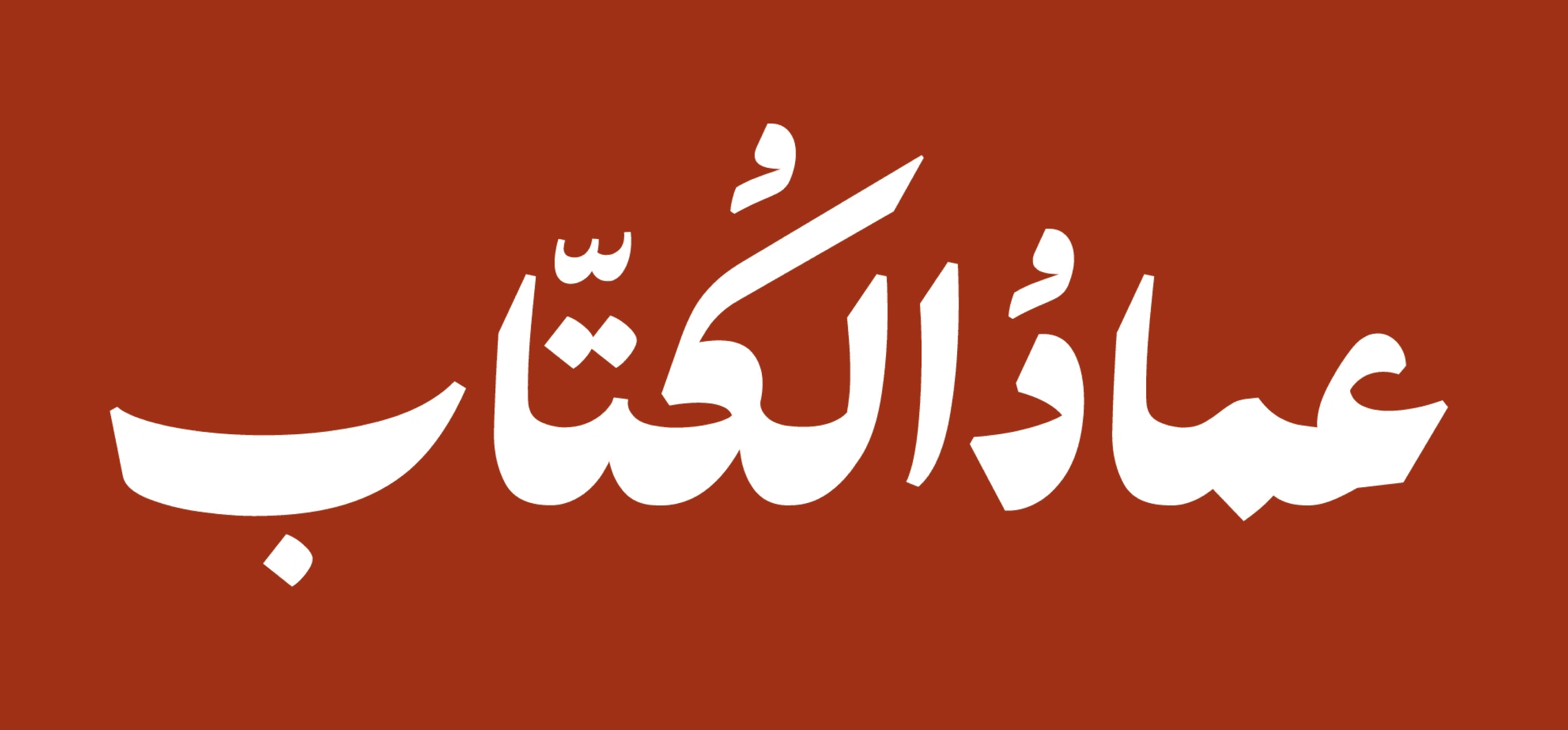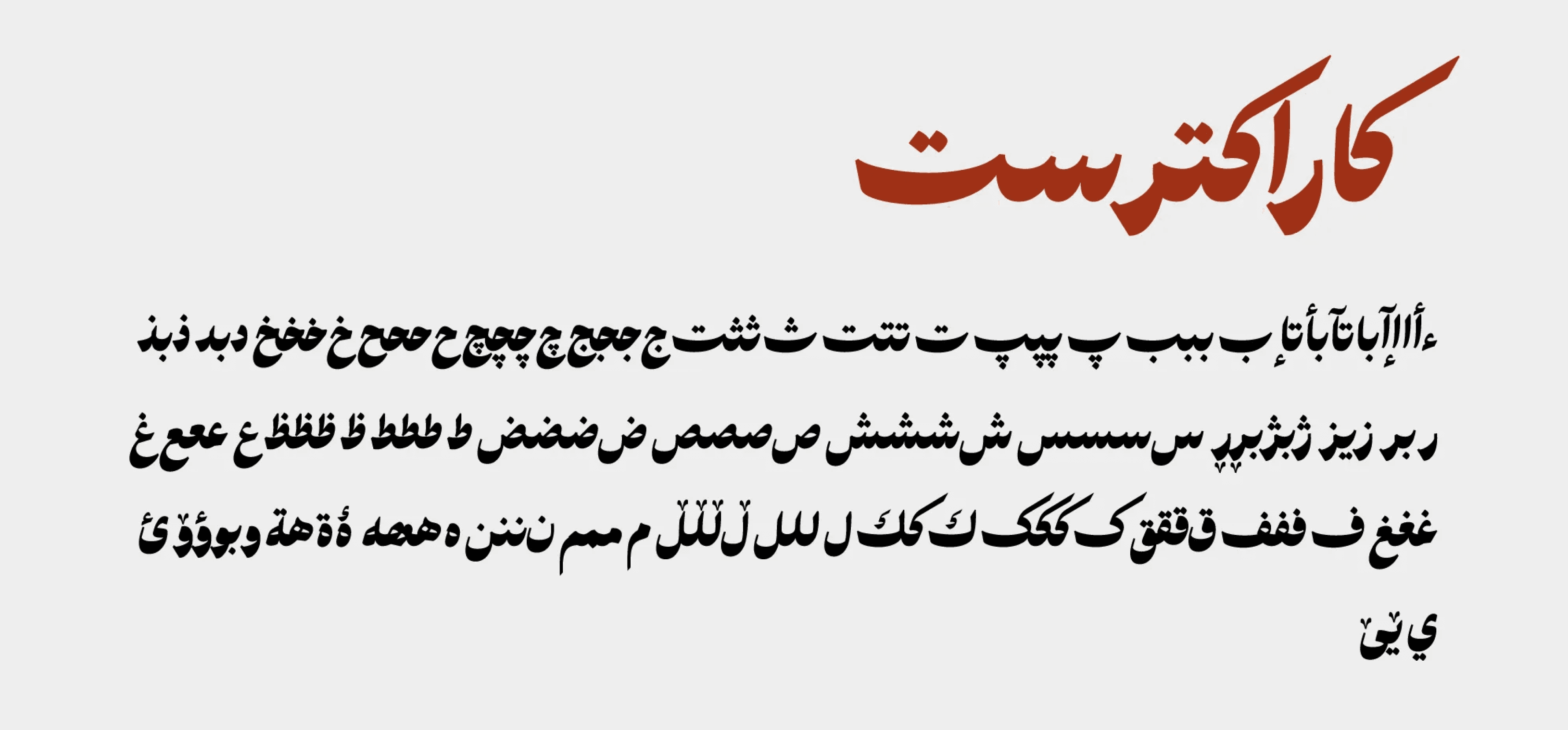
خط "پسته" هو تصور شخصي وإبداعي برؤية عصرية لخط النسخ التعليق (نستعليق). يسعى هذا الخط إلى تقديم مزيج من جماليات التراث وسحر الحداثة للمصممين والمشتغلين بالطباعة. في "پسته"، يلتقي الفن الكلاسيكي والتقليدي مع التصميم المعاصر، حيث تضيف الانحناءات وتفاوت السماكات، إلى جانب الدمج بين الزوايا والأشكال الانسيابية، طابعًا جديدًا وحيويًا على الحروف ليمنح المشاهد إحساسًا بالتدفق والحركة.اطرح سؤالك على ChatGPT